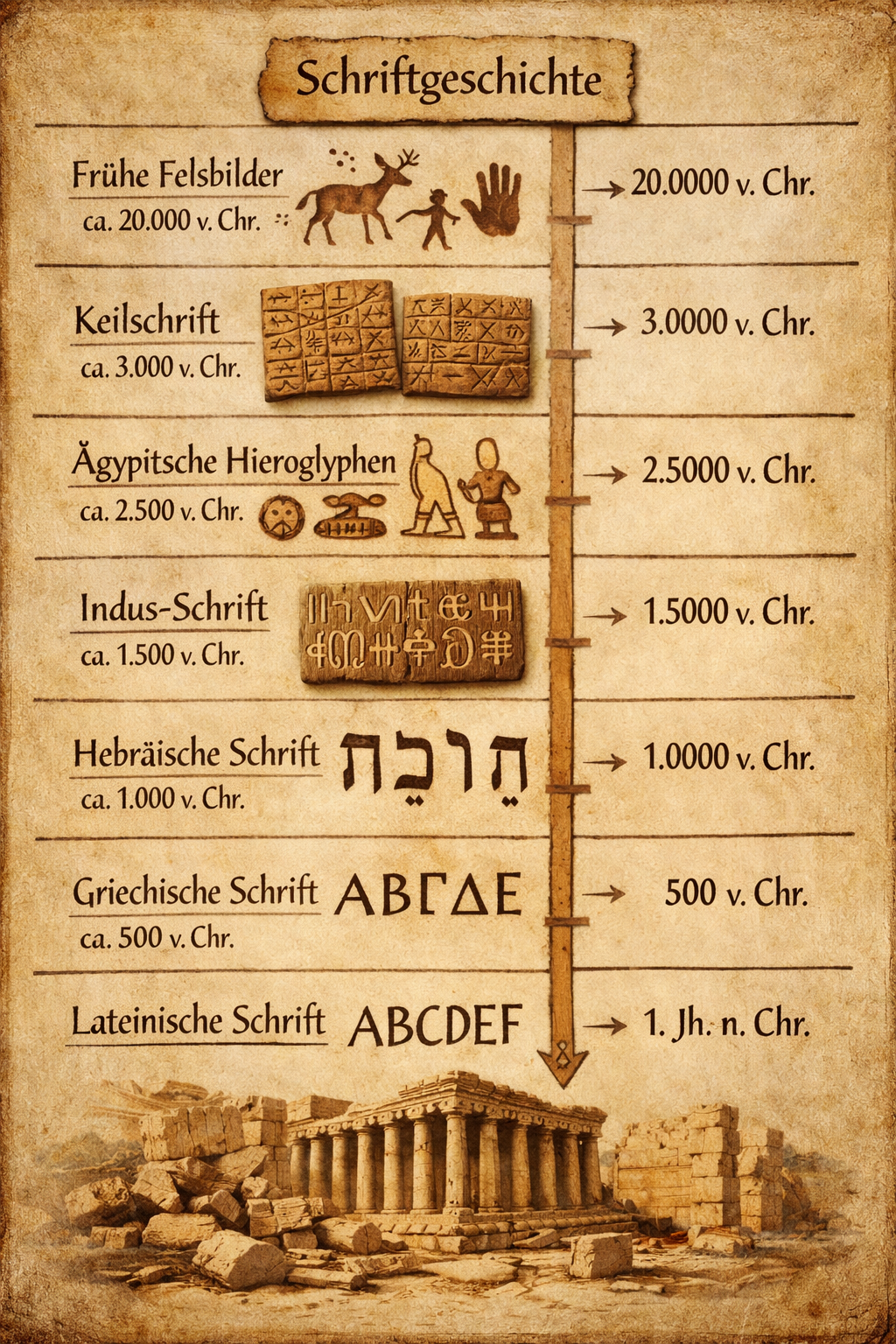
Die frühen Schriften der Menschheit sind eng mit den großen Hochkulturen verbunden: Sumer und Babylon im Zweistromland, Ägypten am Nil, Israel und Phönizien an der Levante. Aus ihren Zeichen wuchsen über Jahrhunderte die Schriften, die später ganz Europa prägten — die griechische und die lateinische Schrift.
Frühe Schriften
Lange bevor unser Alphabet entstand, schrieben die Menschen mit Bildern und Zeichen auf Ton, Stein und Papyrus. Die ersten fünf Etappen der Schriftgeschichte führen von der Keilschrift bis hin zu Griechisch und Latein.
Eine Zeitleiste
Fünf frühe Schriften